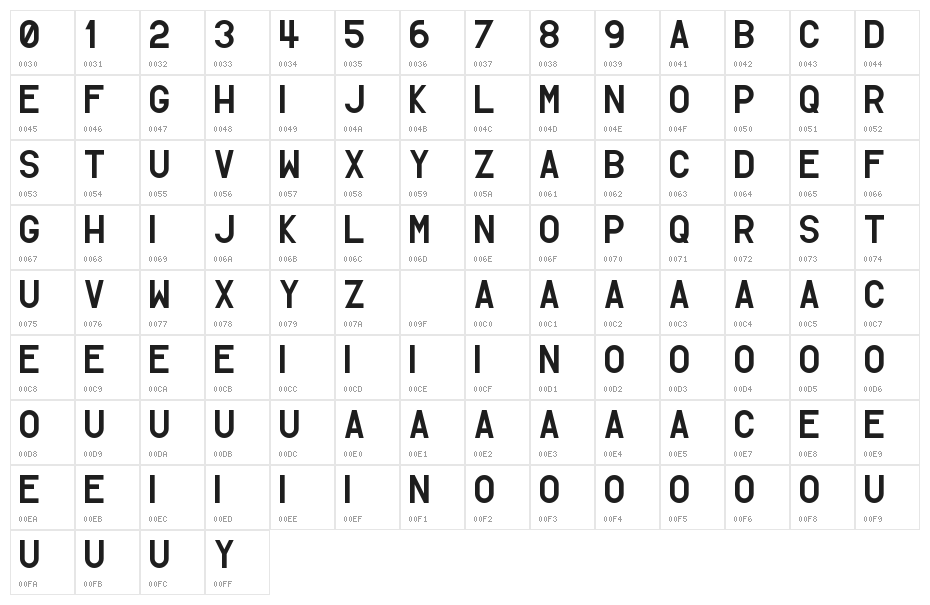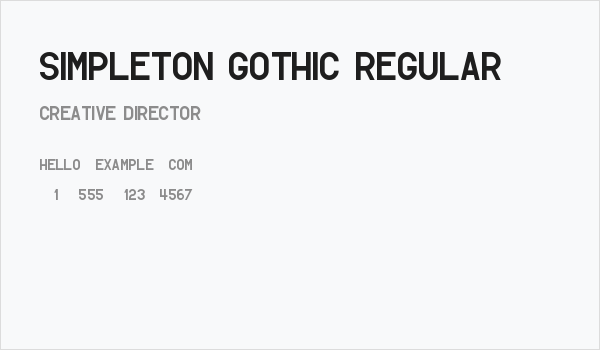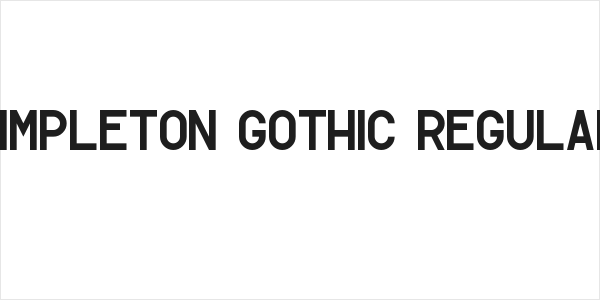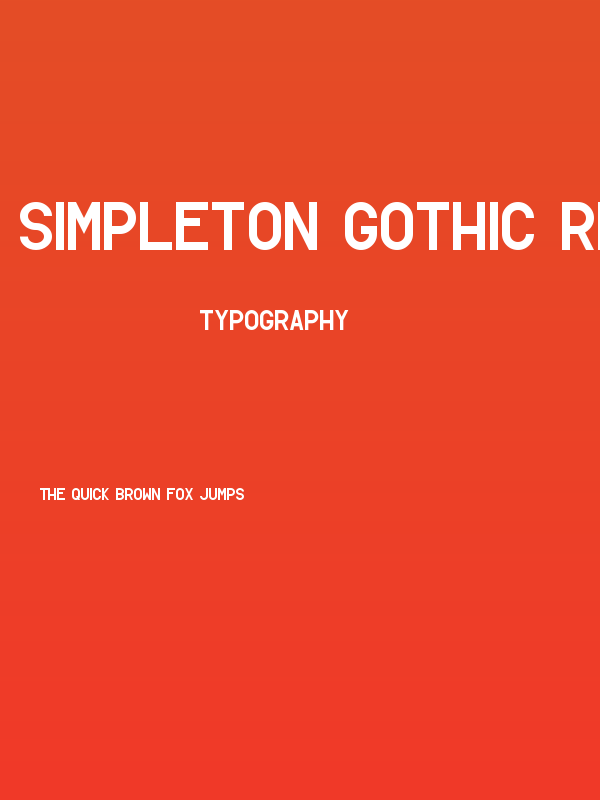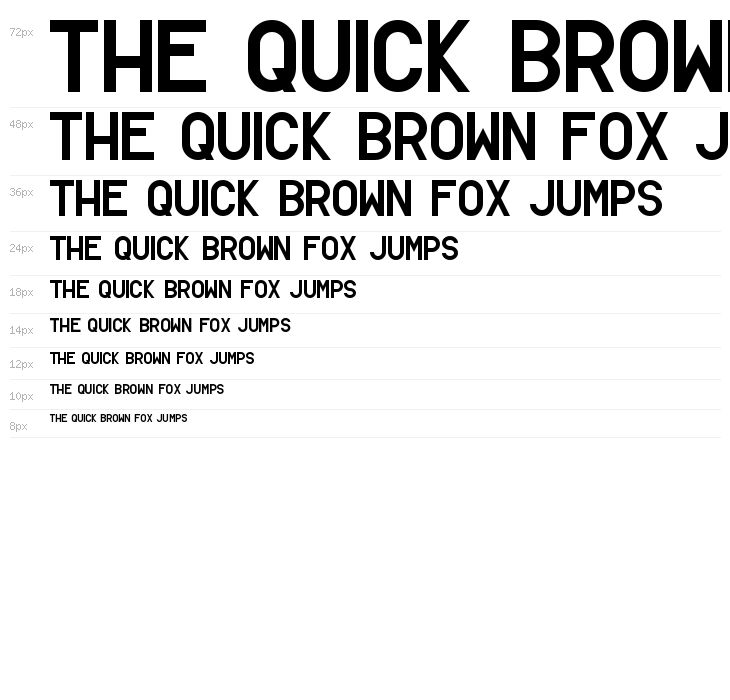
Simpleton Gothic Regular Font
Questo font include 122 caratteri. Clicca su un carattere per vedere i dettagli.
| Caso d'uso | Headlines, Logos, Signage |
| Progetti proposti | Ideal for branding, advertising, signage, and digital interfaces where a strong and clear typeface is required. |